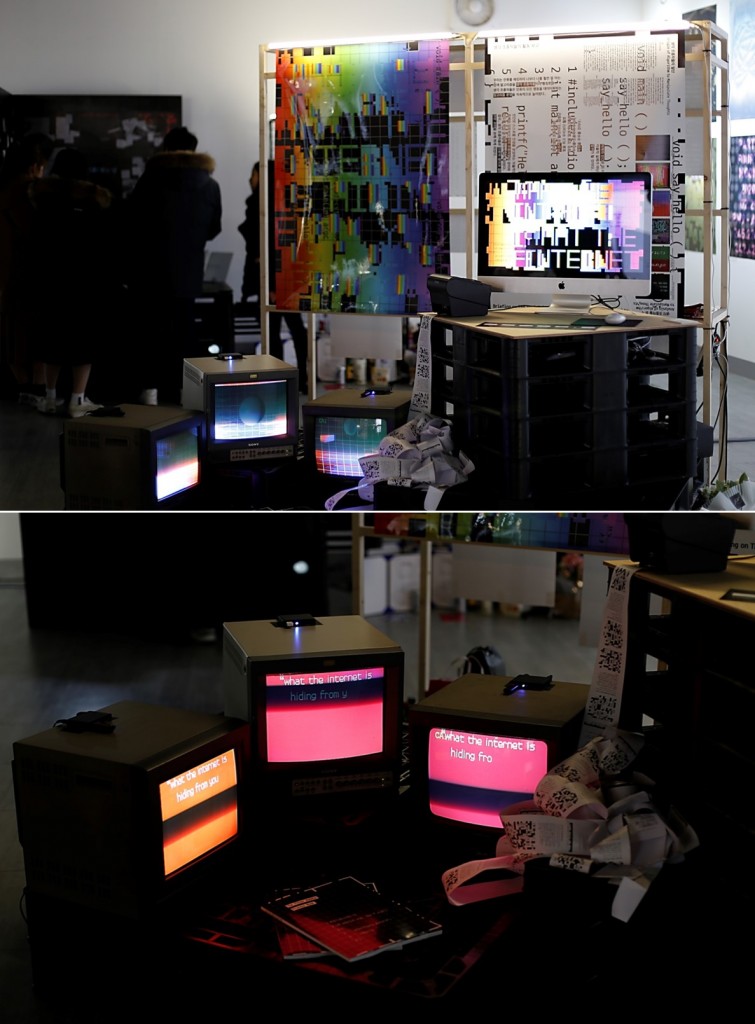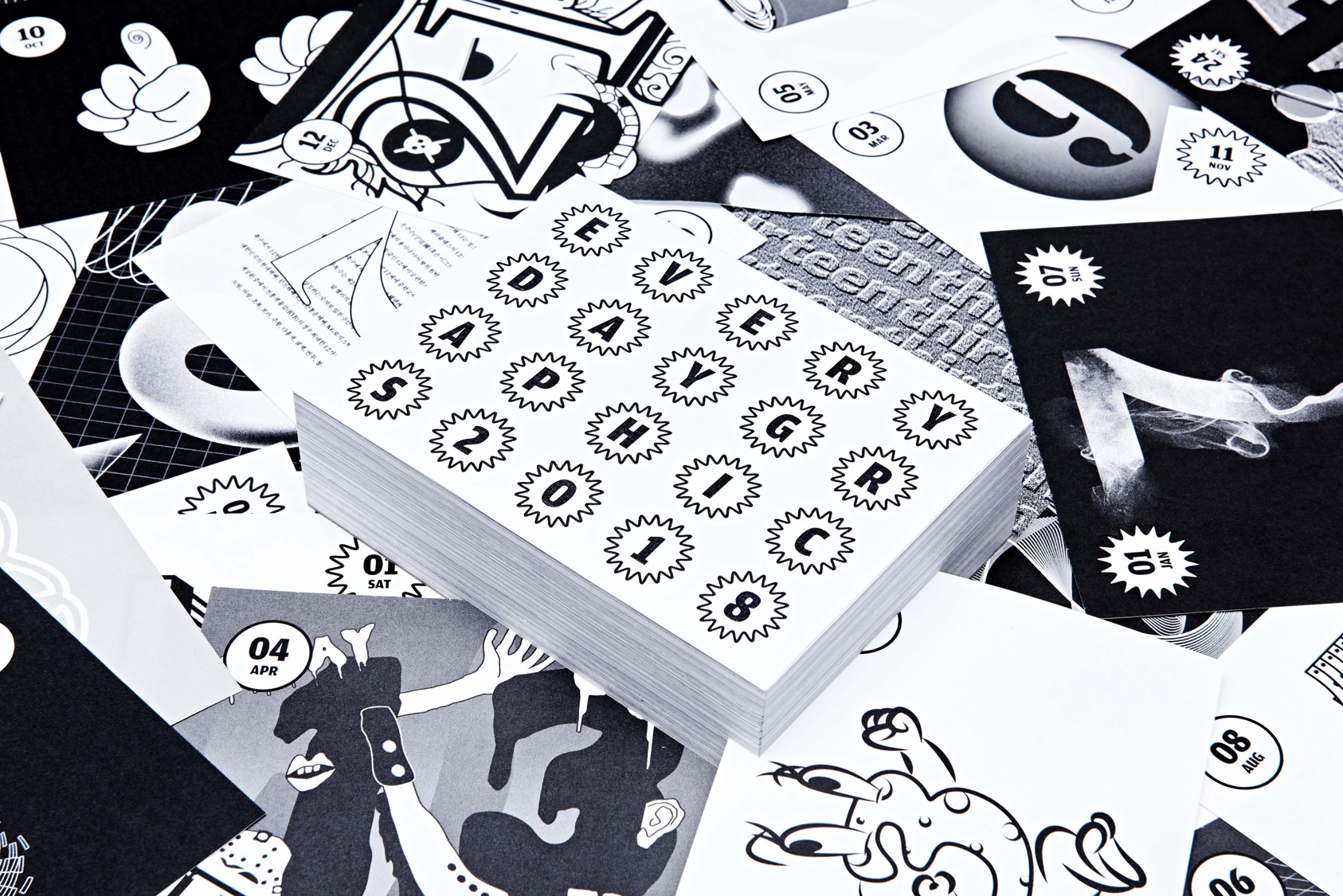
2018 뉴욕 타입 디렉터스 클럽 우수 작품 수상작 ‘The Filter Bubble’/사진제공=국립한경대학교
디자인학과 강유선, 곽민영, 김민지, 황다은 학생의 협업 작품인 ‘생각 조종자들(The Filter Bubble)과 학과의 전원이 공동 제작한 ‘2018 일력(EVERYDAY GRAPHICS)’이 2018 뉴욕 타입 디렉터스 클럽 학생 부문 우수작품상을, 김나무·하주현 교수는 우수 지도자상을 각각 받았다.
두 교수에게 타이포그래피란 자신에게 어떠한 의미로 다가오는지에 대해서도 물었다.
Q. 두 분의 삶과 일상에 ‘타이포그래피’란 어떠한 의미이며 무엇인가요?
“문자언어로 소통하기 위한 가장 기본적인 태도이자 예의라고 생각해요.”(김나무)
“디자인의 기본이자 전부가 될 수 있을 만큼 중요하다고 생각해요. 기초 수업에서뿐만 아니라 심화 수업에서 매 시간 강조할 정도로 시각 커뮤니케이션에 있어 글자와 활자가 차지하는 역할이 크지요.”(하주현)
Q. 수상작에 대해 간략한 소개를 부탁드려요.
“2018 Everyday Graphics는 그래픽 일력 제품입니다. 매일매일 새로운 그래픽으로 하루를 시작한다는 아이디어를 바탕으로 제작하였으며 각 페이지의 그래픽은 해당 날짜에 대한 숫자를 조형적으로 실험한 타이포그래피 결과물입니다. 71명의 한경대 디자인과 3, 4학년이 참여하여 365개의 그래픽을 제작했습니다.”(하주현)
2018 일력(EVERYDAY GRAPHICS), 뉴욕 타입디렉터스 클럽 우수 작품상 수상작/사진제공=국립한경대학교
수상작 <생각 조종자들: The Filter Bubble> (강유선, 곽민영, 김민지, 황다은의 협업 프로젝트)은 인터넷 검열 및 조작이라는 사회적 이슈를 그래픽 디자인의 관점에서 비판적이고 입체적으로 풀어낸 관객 참여형 작품이에요. “(김나무)
이번 수상은 타이포그래피 선진국인 미국에서 한국의 타이포그래피 디자인 실력의 우수성을 인정받은 결과라는 것이 학교 측 설명이다. 이러한 수상 이력을 바탕으로 앞으로의 한경대 디자인학과의 행보에 귀추가 주목된다.